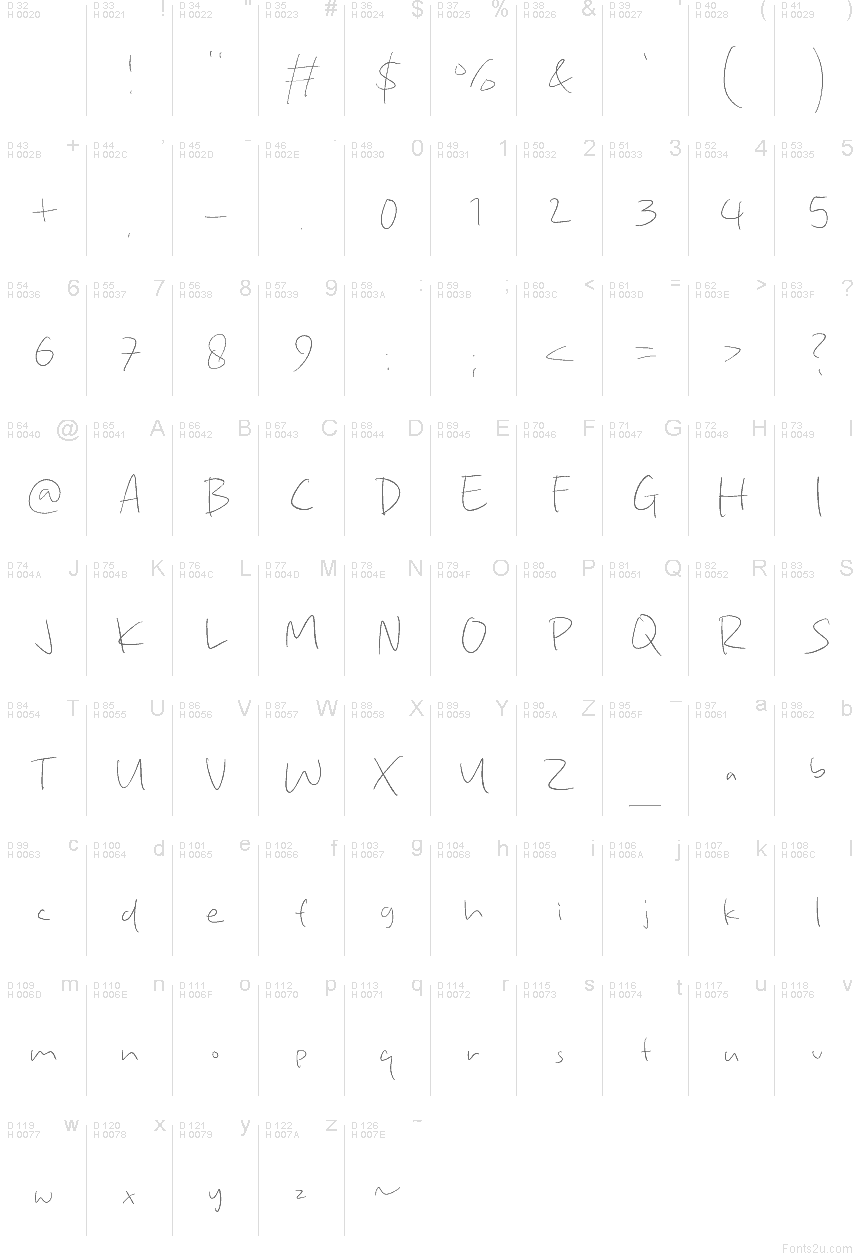
Velschedule Time
Velschedule Time di Origin Type è un font scritto a mano gratuito che richiama la naturalezza di un appunto preso al volo. Le lettere sono leggere e ariose, e combinano tratti lunghi e rilassati con forme semplici, mantenendo una scrittura dall'aspetto casual e non troppo artefatto.
Si adatta perfettamente a titoli per inviti, branding in stile diario, packaging di caffetterie, grafiche con citazioni e brevi post sui social, dove l'obiettivo è trasmettere un senso di personalità piuttosto che di formalità. Usalo per copertine, titoli o piccoli accenti simili a una firma quando vuoi che il testo appaia spontaneo e informale.